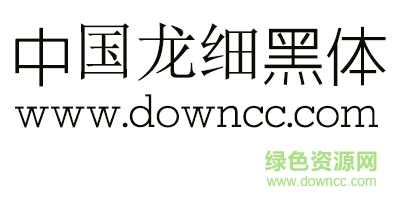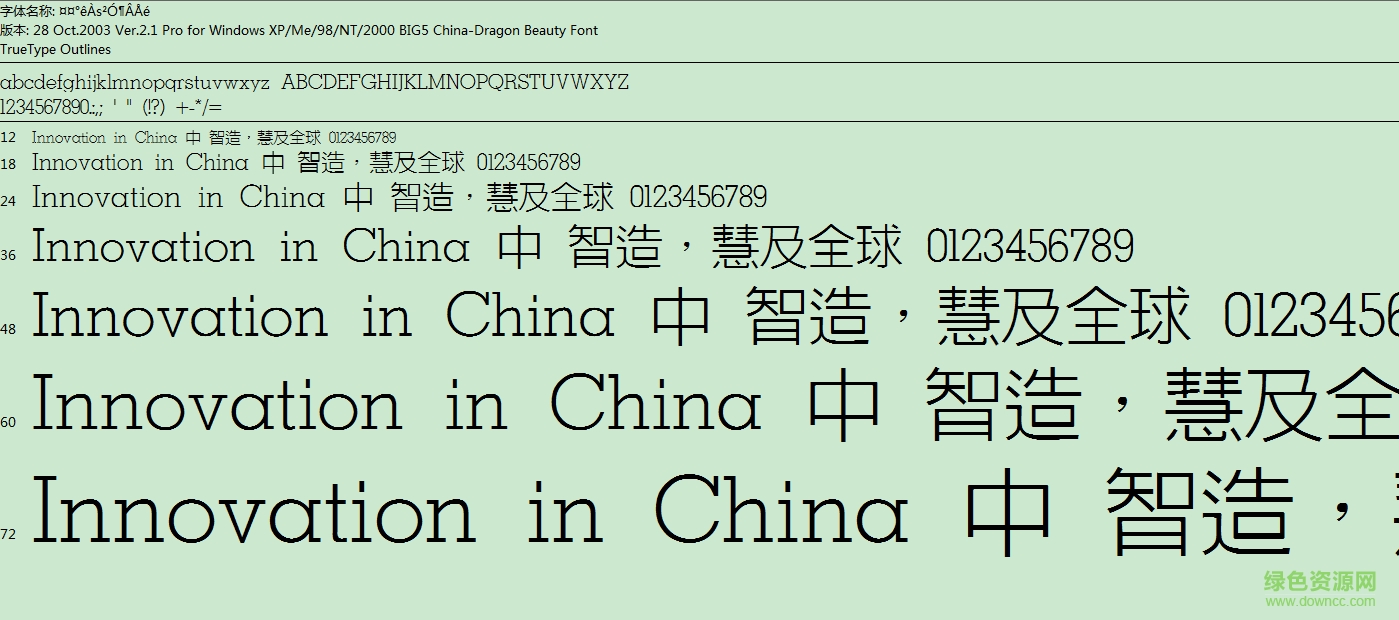
中國龍細(xì)黑體是一款免費(fèi)的黑體字體文件。這款字體很適合進(jìn)行廣告設(shè)計、印刷排版設(shè)計使用。字體線條比較纖細(xì),字體整體上很規(guī)范!歡迎用戶下載安裝使用。
中國龍細(xì)黑體是中國龍字體庫中一種字體,常用于美工設(shè)計方面,字體栩栩如生,喜歡的朋友可以來綠色資源網(wǎng)下載喲!
黑體字是現(xiàn)代漢字體系中最重要的字體之一。尤其是隨著20世紀(jì)末電腦和互聯(lián)網(wǎng)的普及,黑體字的價值得到了進(jìn)一步體現(xiàn),它簡潔的筆畫特征與屏顯介質(zhì)特性相符,從而成為了當(dāng)今各種屏幕媒介中最有發(fā)展前景的字體。但是,關(guān)于這款字的專案研究,迄今為止尚付闕如,關(guān)于它的源起(產(chǎn)生的時間、地點(diǎn)、樣式)更是沒有準(zhǔn)確答案。對這些問題的忽視使得黑體字設(shè)計及其應(yīng)用變成缺少歷史參照的無本之木、無源之水,嚴(yán)重制約著黑體字的發(fā)展。本研究旨在針對中國黑體字起源這個重要問題進(jìn)行系統(tǒng)、詳盡的歷史梳理,為當(dāng)代情境下黑體字的設(shè)計與應(yīng)用提供基礎(chǔ)理論參考。